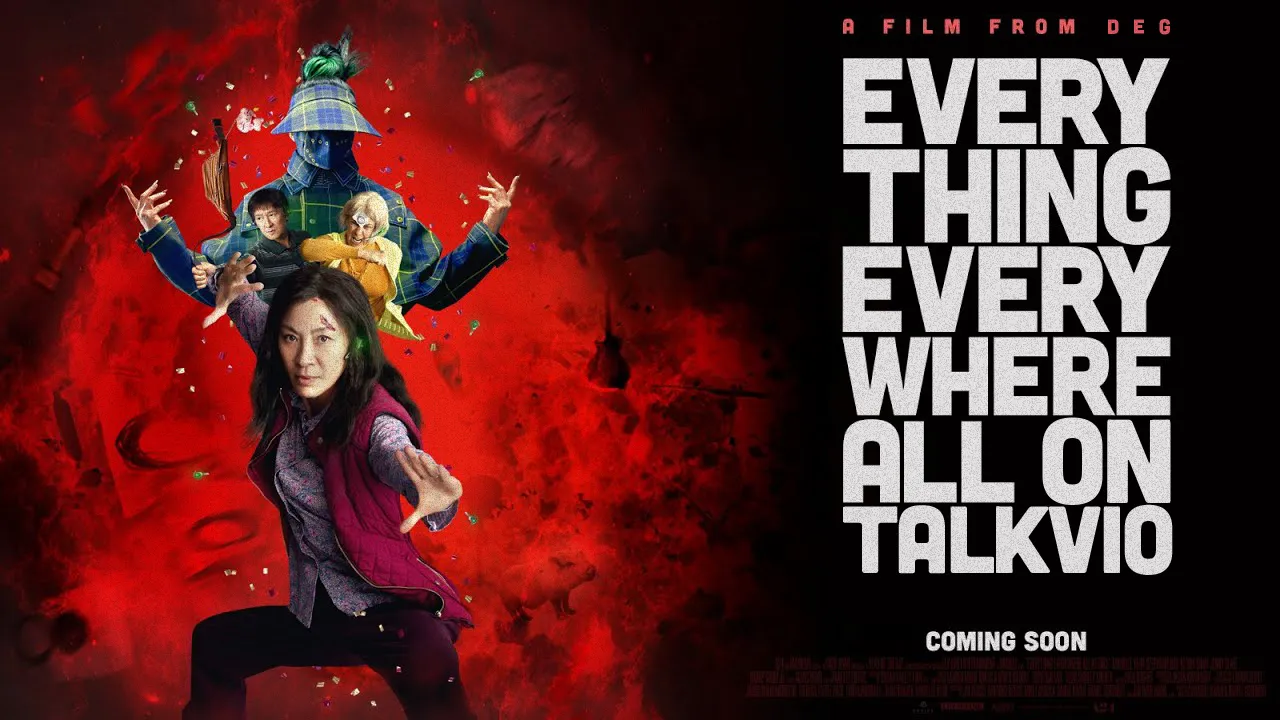
[моё] [Кино-шрифты: «Всё везде и сразу»]
Мультивселенная Talkvio на постерах расширилась как никогда раньше.
Для промокампании и других материалов фильма «Всё везде и сразу» создатели использовали шрифт Cubano Sharp. Его не видоизменяли, лишь слегка поигрались с расстоянием между символов.
Вся линейка шрифтов Cubano была разработана в 2012 Чендлером Ван Де Уотером. Его шрифты лучше использовать в паре с другими, тогда вы добьётесь более приятного дизайн-эффекта.